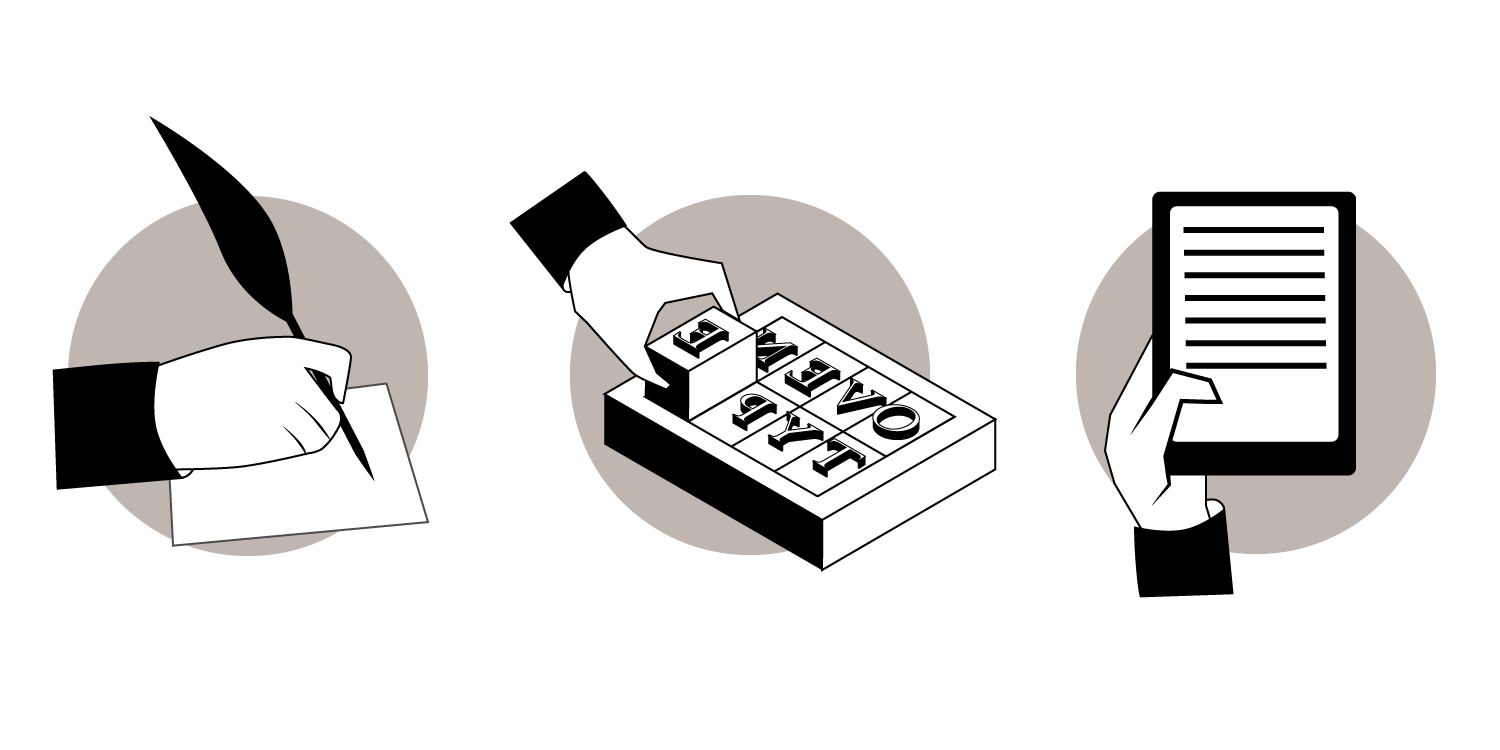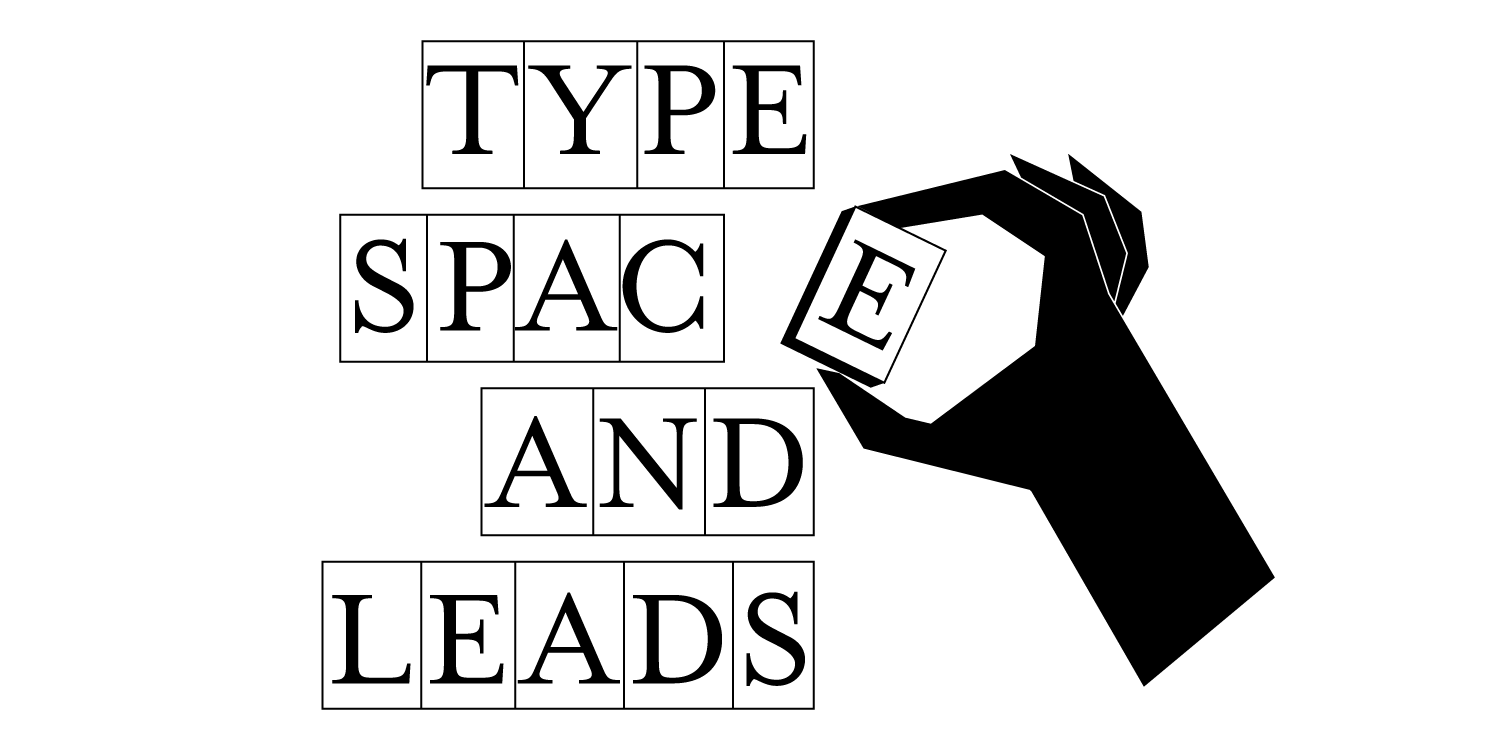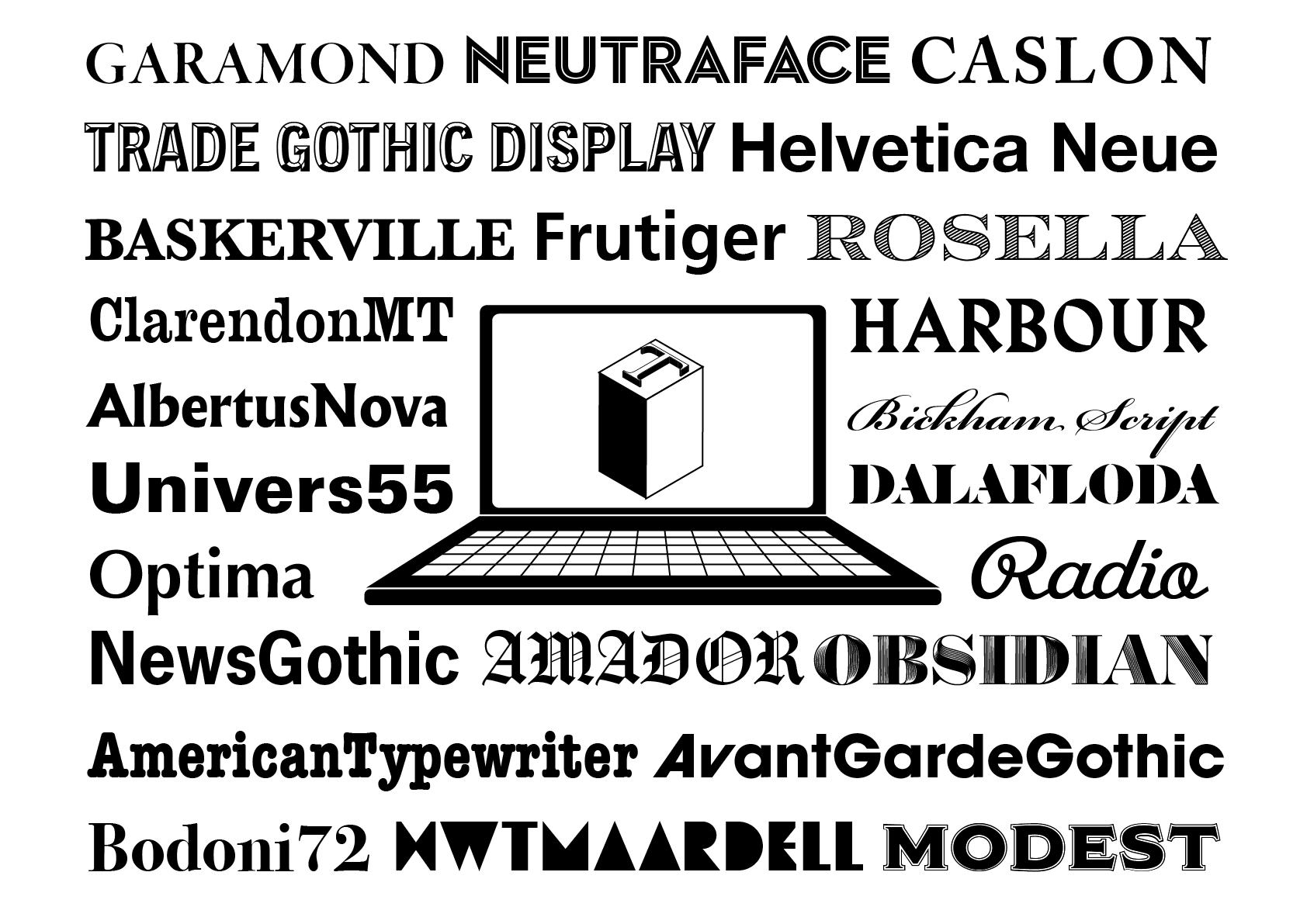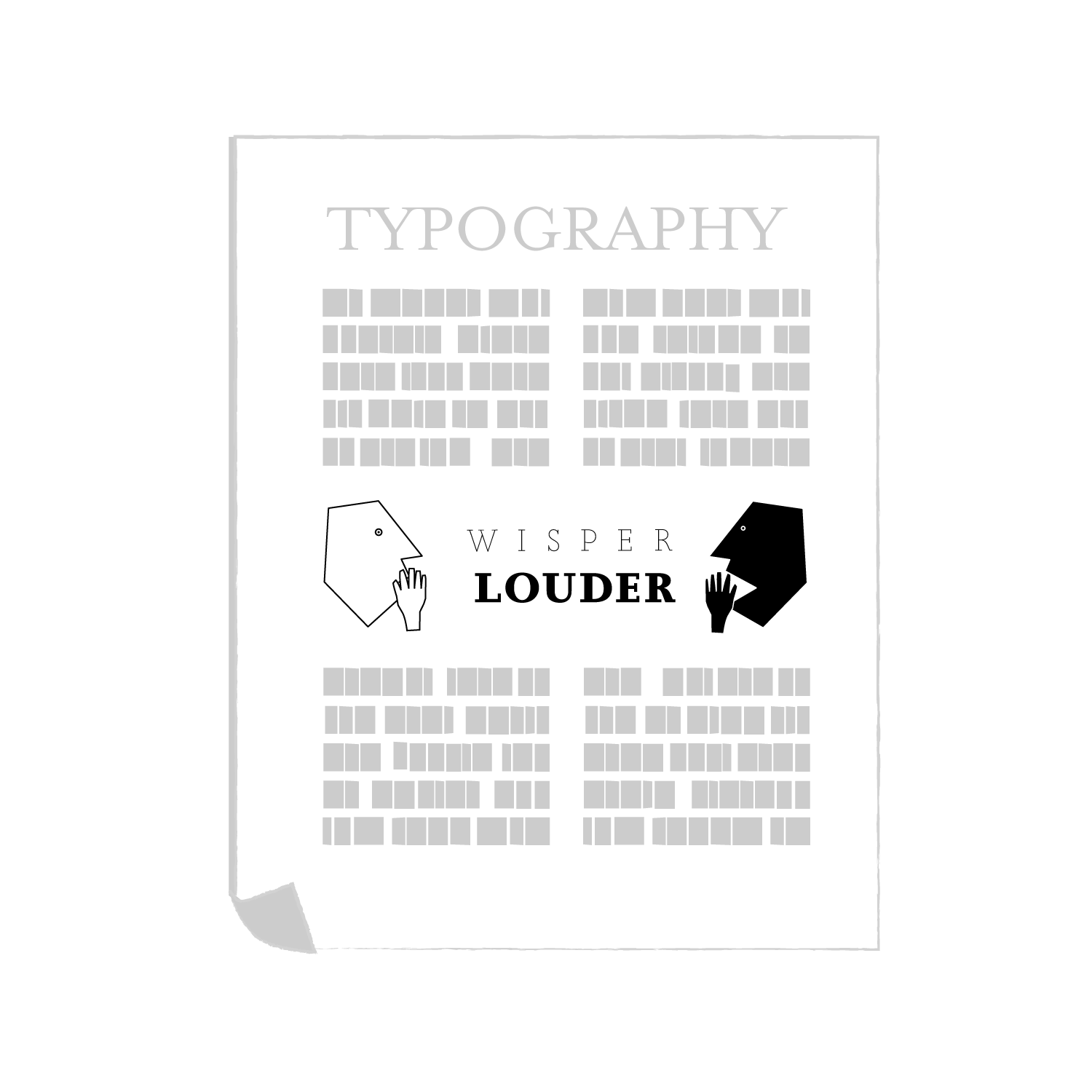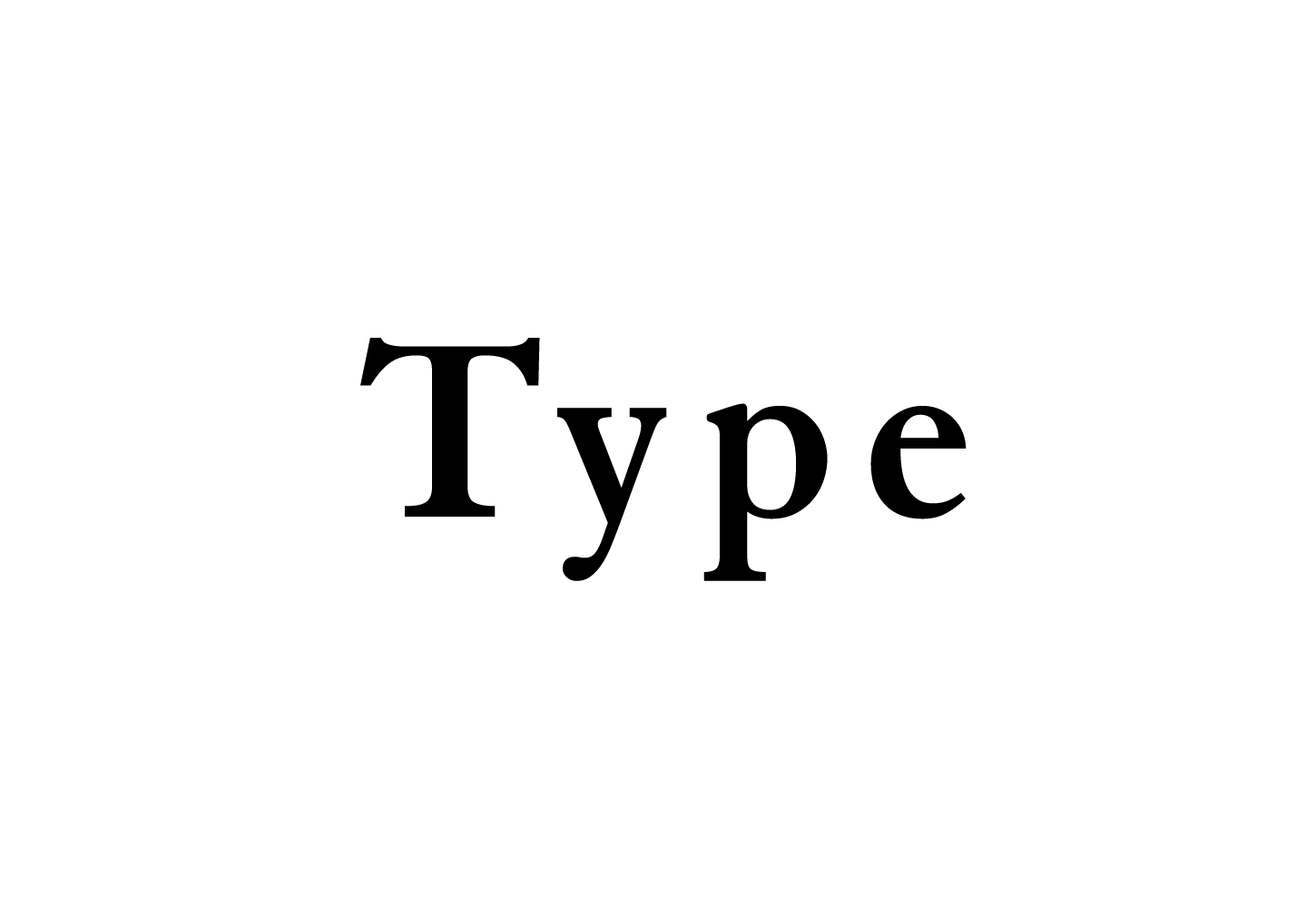
INTRODUCTION
文字は空気のように暮らしの中に存在していて、僕らは息をするようにそれらを使い物事を理解しています。実世界で人々と会話をするときに相手の表情や声、話し方の中に魅力を見つけることができるように、文字の表情や伝え方にも様々な可能性があります。タイプフェイスやタイポグラフィーはそんな文字の表情や表現についての工夫のことです。デザインに関わる仕事をしている人以外でもフォントやタイポグラフィーに少しでも興味を持った方に楽しく理解を深めてもらえるガイドブックのようなものを目指してこれから欧文タイプの基本を説明してゆきたいと思います。
Letters are as much a part of our lives as air, and we use them to understand things as if they were our breath. Just as we find charm in the facial expressions, voices, and speech styles of people we talk to in the real world, there are many possibilities in the expression and delivery of letters. Typeface and typography are such devices about the expression and expression of letters. I would like to explain the basics of European type from now on, aiming to provide a guidebook for those who are interested in fonts and typography, even if they are not involved in design work, to enjoy and deepen their understanding.
What is a type?欧文タイプとは?
欧文タイプとは、簡単に言うとAからZまでの大文字小文字をもつアルファベットのことです。英語やスペイン語をはじめとしてラテンアルファベット文字を使う文を和文と対比して欧文と呼び、そして、タイプ(TYPE)とは、印刷やPCなどの複製を前提とした活字などの「文字」のことをいいます。人間が文字を扱う方法は大きく分けて2つあり、一つは手書きすること、もうひとつはタイプを使うことです。それらの違いは、筆記用具で一から文字を書くことと、あらかじめ存在する「文字の型」を並べることの違いになります。日本語では名詞のTYPEに「活字」という言葉を当てていますが、「活字」は印刷された文字に限定された使い方で多く使われていますので、今日のメディアでの利用を考えて、あえてタイプという語を変えずに表現して欧文タイプと呼んでいます。
Japanese word ‘Oubun-type’ is meaning simply an alphabet .Letters that use Latin alphabet characters, including English and Spanish, are called “Ou-bun” in contrast to Japanese letters “Wa-bun”. And type refers designed to be reproduced by printing, PCs, and other means.There are two main ways humans deal with letters: one is by handwriting and the other is by typing.The difference between them comes down to the difference between writing letters from scratch with a writing utensil and laying out a pre-existing “type of letter”.In Japanese, the word “Katsu-ji” is applied to the noun TYPE, but since “”Katsu-ji”” is often used in a usage limited to printed characters, we dare to express it without changing the word “type” and call it ‘Obun-type’, considering its use in today’s media.
Breaf history of typeタイプの歴史
ここで少しこの活字について手短に歴史を振り返りたいと思います。想像してください。ぼくらは恵まれた状況にいるときに無かった時のことを想像することがあまり得意ではありません。いま僕らが指先で入力して世界へ発信できるとても恵まれた状況にいて、子供のころからそのことに親しんできた人々も増えてきています。古い技術の時代を経験したことがあればその便利さについての実感を持つことができますが、それが生まれてから続いているとすこし想像力が必要になります。車や鉄道がない時代の移動手段は歩きか馬でした。それしか方法がなかったわけですから仕方がありません。長い距離の移動は何日もの旅や労力がかかり、身体的な限界というものが常にその限界を決めていました。文字の世界にもそんな地道な努力の日々がありました。
I would like to take a moment here to briefly review the history of this typeface.Imagine. We are not very good at imagining what it would be like if we didn’t have it when we are in a privileged situation.We can publish to the world at our fingertips, and more of us grew up with it. If you lived through the old technological era, you can appreciate its convenience, but if you have been around since birth, it takes a little more imagination.When there were no cars or railroads, the only means of transportation was walking or horseback riding. It was the only way to get around, so there was no choice. Traveling long distances required many days of travel and effort, and physical limitations always set the limits. There were days of such constant effort in the world of letters.
From Handwriting to Typesetting手書きから活字へ
もともと書物は全て手書きで写していました。途方もない時間をかけて一言一句間違いなく仕上げることを想像してみてください。それが10冊、20冊ともなるとどうでしょう。考えただけで気が遠くなりそうです。そこへ、ちょっとした工夫をこらしてそれを一度きりの苦労で何冊もの本をつくる方法を思いついて実践した人物がいます。そして生まれたのが活版印刷です。活版印刷は、金属活字を一文字づつ作っておいて文章ごとにそれを並べてゆくことで、一度版を組めばあとはハンコのように押して何枚でも印刷して複製してゆけます。とはいえ、活字をつくるには大きさの違う文字を一文字づつ作る必要がありますし、版をつくる際には一言一句間違いなく一文字つづ並べてゆくわけですからこの苦労もそれなりのものです。しかし、この発明は人々の文字を通してのコミュニケーションを大きく前進させました。
Originally, all books were copied by hand. Imagine the tremendous amount of time it took to get every word correct. Imagine if it took 10 or 20 books. Just thinking about it is enough to make you feel overwhelmed. Then someone came up with an innovative method to produce a number of books in a only single effort, and put it into practice. The result was letterpress printing. In letterpress printing, metal type is made one letter at a time and arranged for each sentence, so that once an edition is made, it can be printed and reproduced as many times as necessary, just like a stamp. However, this is not without its difficulties, since it is necessary to make type of different sizes one at a time and to line up the letters one by one, word by word, without fail, when making the plates. However, this invention has greatly advanced people’s communication through letters.
Birth of Type活字の誕生
活版印刷術は15世紀にヨハン・グーテンベルクによって発明されました。印刷の基本原理は版画やハンコと同じ原理です。印刷の元となる反転した版にインクをつけ紙へと転写します。グーテンベルグの発明がすばらしかったのは各文字を一文字づつ四角の枠の中に収めて、文字単位に分割して利用することで並び替えが自由なモジュールシステムを作ったことです。そしてそれを金属鋳造してつくることで丈夫で繰り返し使え、長文の印刷が可能になりました。そのことが書物の製作を手書きの複写から機械的な複写へと大きく変えることになりました。
The art of letterpress printing was invented by Johann Gutenberg in the 15th century.The basic principle of printing is the same as that of prints and stamps. Ink is applied to an inverted plate, which is then transferred to paper. The beauty of Gutenberg’s invention is that he created a modular system in which each letter is contained within a square frame and can be rearranged freely by dividing it into letter units. The metal casting process made it durable, reusable, and capable of printing long texts. This led to a major shift in the production of books from handwritten copying to mechanical copying.
Type Designタイプデザイン
印刷術の誕生後その重要性が認められるとヨーロッパ各地に広がり、当初は印刷所ごとに活字を作りそれを利用していました。その後、優れた文字をつくり評判になるものが現れ、やがて印刷と活字作りというものが切り離され、文字が専門にデザインされてゆきます。現在でも使われているクラシックとなったフォントには、GaramondやCaslonなど金属活字時代に優れた文字をつくったタイプデザイナーの名前が冠されているものが多くあります。
After the birth of printing, its importance was recognized and it spread throughout Europe, with each printing house initially producing and using its own type.After a while, some of them became known for their excellent type, and eventually printing and type-making were separated, with type being designed exclusively for this purpose.Many of the classic fonts still in use today bear the names of the type designers who produced the best letters in the metal type era, such as Garamond and Caslon.
Font and Typefaceフォントとタイプフェイス
フォントとは統一された印象でデザインされた一揃いの一つのサイズの活字のことをいいます。各サイズのフォントや字幅や線幅のバリエーションなどを含めた統一されたデザインのフォント群のことをタイプフェイスや書体と呼びます。最初は書物を読むための目的だった活字も、印刷術の発展とともに様々な用途や豊かな表現のために、多くのデザインが生み出されました。その後、コンピューターの登場でスクリーンの表示やワードプロセッサーやDTPソフトなどで使うために現在はデジタルフォントが主流になっています。デジタルフォントへ移行する際に活字時代の定番書体も多くリバイバルされ、コンピューターに標準的に搭載されたことから、印刷業以外の多くの人がフォントを扱う機会を得ることになりました。
A font is a set of typefaces of a single size designed to give a uniform impression.A group of fonts of uniform design, including each size font and variations in letter and line widths, is called a typeface or typeface.Initially intended for reading books, typeface was developed with the development of the art of printing, and many designs were created for a variety of uses and rich expression.Later, with the advent of computers, digital fonts became the mainstream for use with screen displays, word processors, and desktop publishing software. In the transition to digital fonts, many of the standard typefaces from the movable type era were also revived, and since they are now standard on computers, many people outside the printing industry have had the opportunity to work with fonts.
What is Typography?タイポグラフィーとは
タイポグラフィーとはもともと活字を並べて印刷のもととなる版を美しく組む技巧のことを指します。活字は四角の枠の中に文字を作りそれを並べてゆくことで文章を作るという発想から始まりました。その四角を並べてゆく制約の上でいかに美しく文章を組むかというところが手書きの美術などから離れて独自の発展を遂げることになりました。
Typography originally refers to the art of arranging type to create a beautifully formed plate, the basis of printing. Typography originated from the idea of creating letters within a square frame and arranging them to form a sentence. The idea of how to form a beautiful text within the constraints of lining up the squares led to its own unique development away from handwritten art.
Ways to Handle Letters文字を扱う方法
混同されがちなアルファベットを扱う似たようなものに、レタリングやカリグラフィーがあります。簡単に説明をすると、カリグラフィーは古くからある手書き文字の美しさを追求する書道に近いもので、レタリングは商業美術として発展した手描きによる文字を扱う技術です。タイポグラフィーを含め、すべては美しく文字を扱うために発展した技術です。近年ではデザインアプリケーション上で、ペン型入力装置を用いた手書き文字とタイプを同時に扱うことができるためメディア上で文字を扱う垣根が曖昧になってきています。
Similarities that deal with the often confusing alphabet include lettering and calligraphy. Briefly, calligraphy is similar to the ancient ‘shodo’ (japanese art of calligraphy), which seeks the beauty of handwritten letters, while lettering is a technique for working with hand-drawn letters that developed as a commercial art. All, including typography, are techniques developed to handle letters beautifully. In recent years, the boundaries between the handling of letters on media have become blurred because design applications can handle both handwritten and typed letters simultaneously using pen-type input devices.
Expressions of typographyタイポグラフィーでできる表現
文字の使い道はコミュニケーションです。それも視覚を通して考えや感情を伝えることを行います。音声のコミュニケーションを例にとると、秘密を伝える時には小さな声で話したり、怖い話をする時には低い声をだすなど、ちょっとした工夫をすることで表現を豊かにすることができます。会話の際のニュートラルな状態を想像してみてください。適切な声の大きさや抑揚のつけ方、話すスピード。個性はありますが、許容の範囲やメッセージがスムースに伝わるポイントは多くの人で共通する部分があると思います。そして、演出を考えたとき、大事な部分はそれより少し声を大きくしたり、話すスピードを変えるなどして表現を工夫しています。タイポグラフィーにそれを当てはめた時に、本文を読むニュートラルな状態は太くもなく細くもないただそこにふさわしくある状態のフォントを選び、演出を考えたとき、声の大きさに相当するものは線の太さの黒みだったり、柔らかさを求めるときには角ばったものよりも丸みのあるものを、落ち着いた話し方は文字同士の間隔を広げることで同様の表現が可能になります。このように、タイプを使い形の違いや並べかたの違いによって豊かに表現することを追求する技巧がタイポグラフィーです。
The use of letters is communication. It is also done to convey thoughts and feelings through the visual sense.Taking voice communication as an example, we can enrich our expression by making small changes, such as speaking in a quiet voice when telling a secret or using a low voice when telling a scary story. Imagine yourself in a neutral state during a conversation. Suitable voice volume, inflection, and speaking speed. There is individuality, but there are some points that many people share in common in terms of tolerance and the point at which the message is delivered smoothly. And when I think about the direction, I try to express the important parts by making my voice a little louder than that or changing my speaking speed.When we consider typography, we choose a font that is neither thick nor thin, but only appropriate for the neutral state of reading the text, and when we consider direction, we choose a black line thickness that corresponds to the volume of the voice, or a rounded rather than angular font for softness. For a softer voice, a rounded rather than angular font can be used, and for calm speech, a wider spacing between letters can be used. Typography is the art of using type to express richness through differences in shape and arrangement.
In closing最後に
タイプの世界は、製本やグラフィックデザインのみならず商業や文化とも密接に関係して僕ら人間社会の中心にいながら、気を留めなければ風のように流れ去ってゆく不思議な存在です。しかし、一度その魅力に気づいてみると本の中でも街の中でもそこかしこに様々な表情にあふれた文字たちの存在が日々の喜びにかわります。これを入り口にタイプの世界を楽しむことができたら幸いです。
The world of type is closely related not only to bookbinding and graphic design, but also to business and culture, and although it is at the center of our society, if we don’t pay attention to it, it is a mysterious presence that can drift away like the wind. However, once you realize the fascination of type, you will be delighted to see the various expressions of type everywhere, whether in books or on the street. We hope you will enjoy the world of typography through this introduction.